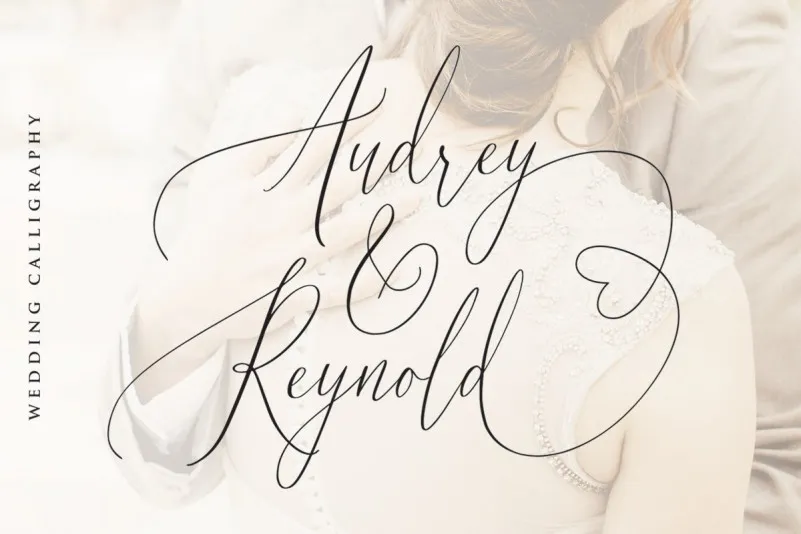
Audrey & Reynold Calligraphy Font – Download Grátis
Introduzimos a nova tipografia para casamentos chamada Audrey & Reynold Font! Ela oferece uma harmonia tipográfica bela para diversos projetos de design. Audrey & Reynold é uma tipografia moderna do calligrafista que adiciona nuances sofisticadas e contemporâneas. Perfeita para a identidade visual de casamentos, cartões de convite e até mesmo rótulos de vinho branco. Esse tipo de fonte tem um design elegante e moderno, criado especialmente para os detalhes exuberantes dos eventos de casamento. Audrey & Reynold é uma opção ideal tanto para criar a identidade visual do seu grande dia quanto para personalizar cartões ou até mesmo rótulos de vinhos especiais. Não importa qual projeto você esteja trabalhando, Audrey & Reynold oferecerá um toque único e sofisticado, tornando qualquer design impecável e encantador.